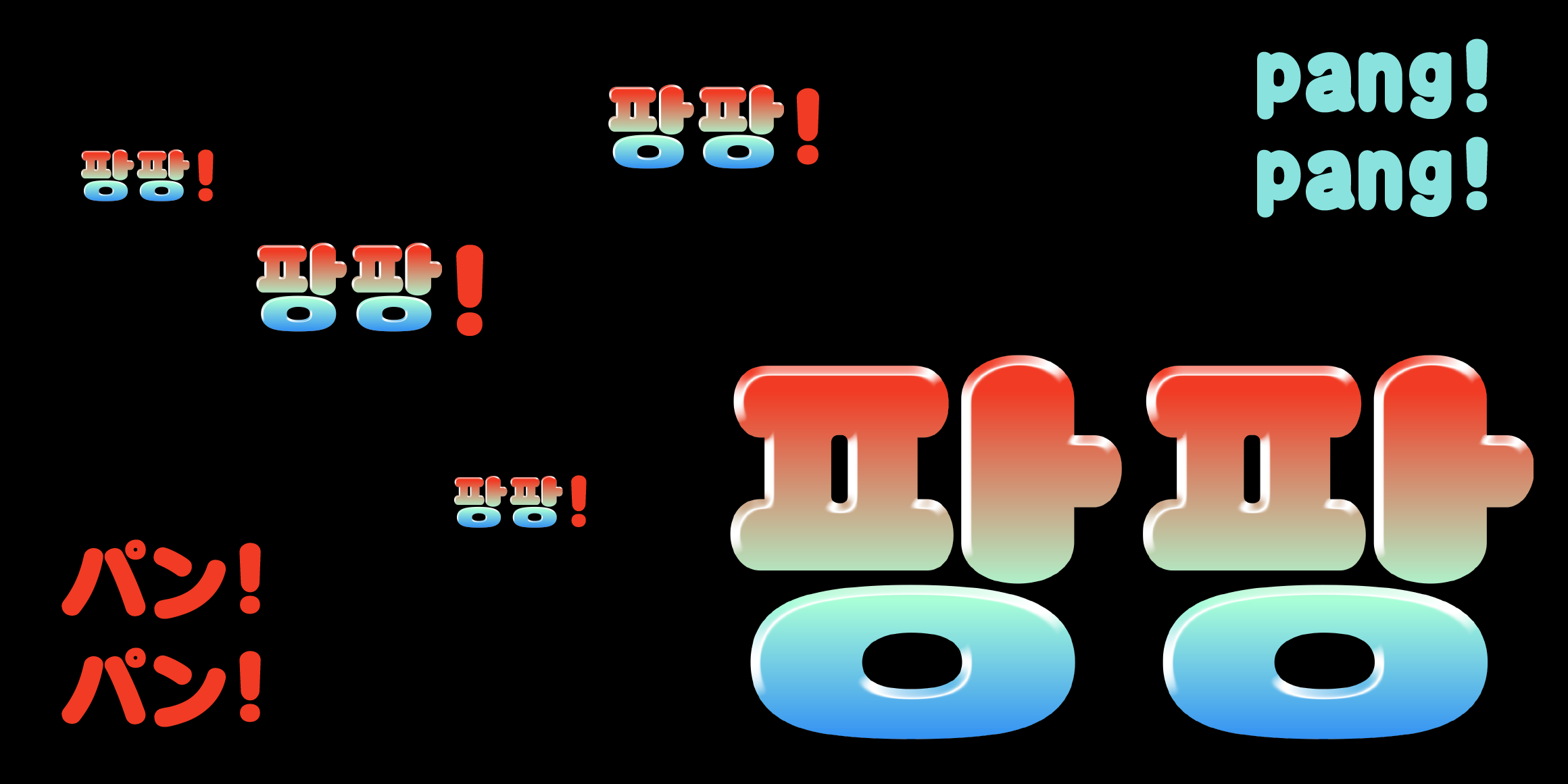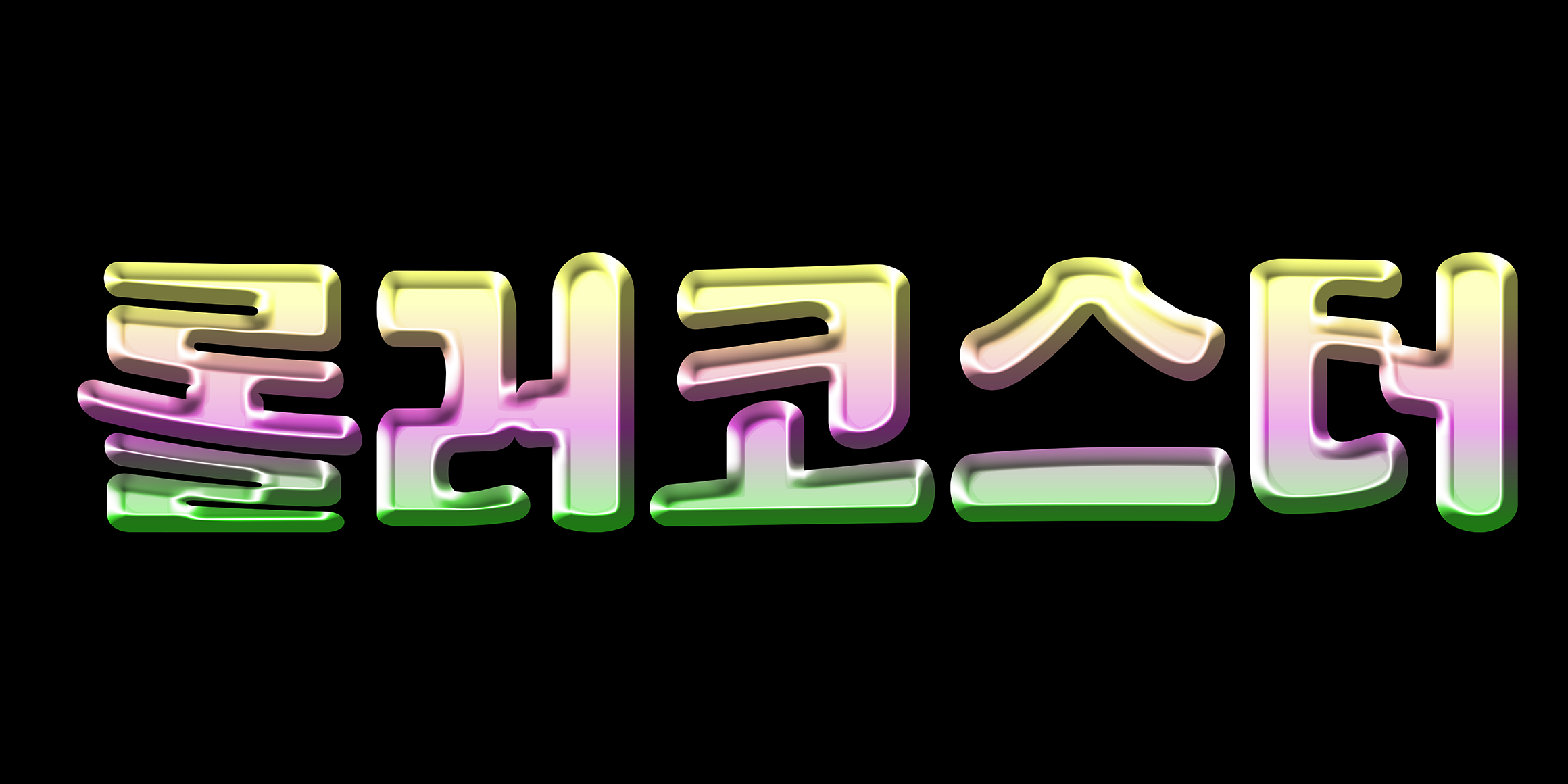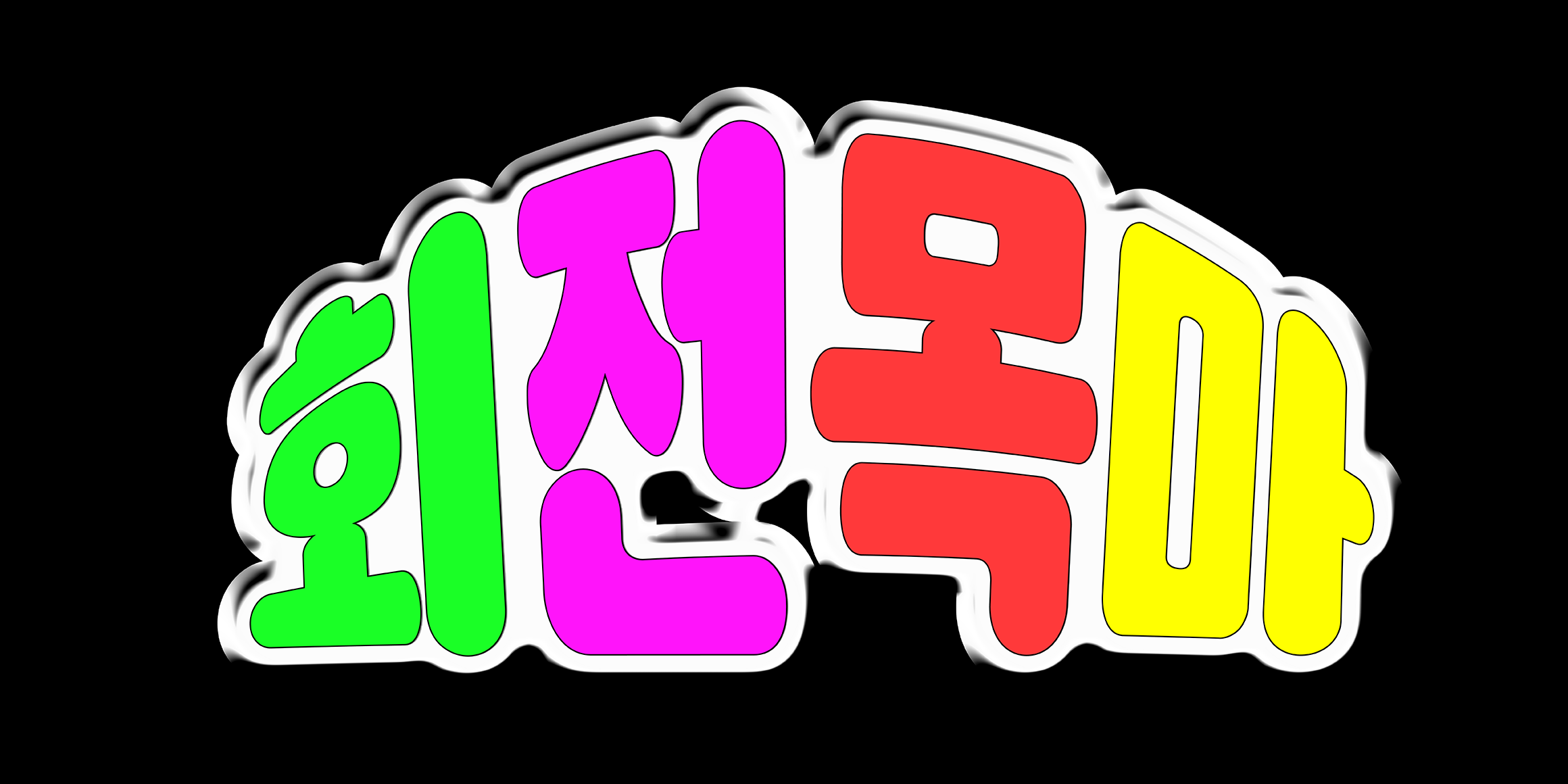
J혜화동벽화
한 글자 안에서도 자소의 획이 서로 일정치 않은 두께로 표현될 만큼 자유로우면서도 다소 불완전한 균형감으로 인해 오히려 예상하지 못한 긴장감을 주는 글꼴입니다. 완만한 곡선의 끝맺음 처리와 넉넉한 두께감으로 포근함과 정겨움이 느껴지는 것이 특징입니다.
• 디스플레이
• J혜화동벽화 / JHyehwadongByeokhwa